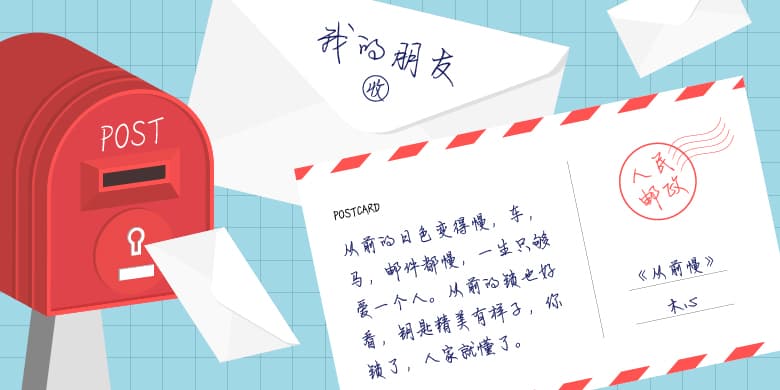
品牌:方正字迹设计师:徐万清发行时间:2020字库编码:大陆简体(GB2312-80)分类:常规书写·硬笔字体属性:精品字
徐万清手写体将传统书法之精华与现代人的审美和书写习惯相结合,特点是结构精美,比例协调、骨骼清秀、笔画洒脱、收放有度,适用于现代诗歌、短文的排版、书写信函、报告、请柬、贺卡、包装印刷以及文化、商业类品牌的广告语设计等。
品牌:方正字迹设计师:徐万清发行时间:2020字库编码:大陆简体(GB2312-80)分类:常规书写·硬笔字体属性:精品字
徐万清手写体将传统书法之精华与现代人的审美和书写习惯相结合,特点是结构精美,比例协调、骨骼清秀、笔画洒脱、收放有度,适用于现代诗歌、短文的排版、书写信函、报告、请柬、贺卡、包装印刷以及文化、商业类品牌的广告语设计等。